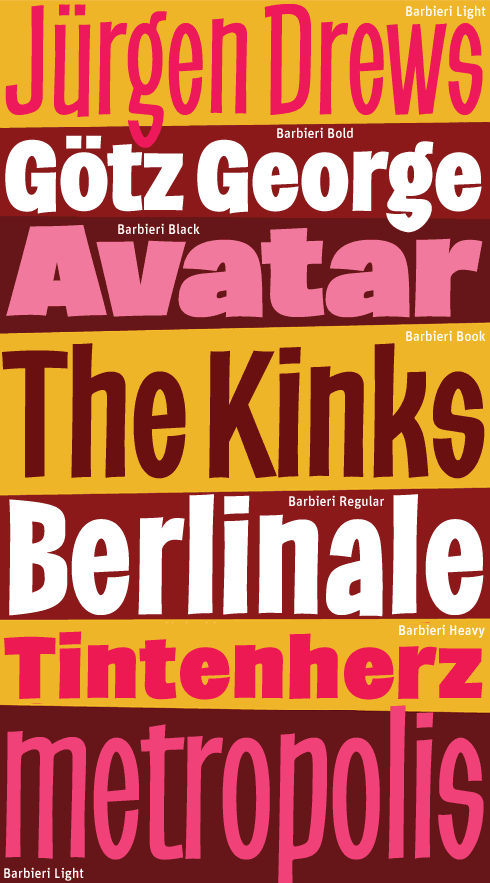
Diese Schriftfamilie braucht nicht viele Worte, deshalb fasse ich mich kurz und stecke meine ganze Energie in das Schriftmuster. Vorlage für Barbieri war eine handgezeichnetes Plakat für eine deutsche Aufführung der Oper »Der Barbier von Bagdad« in den 60er Jahren. Andrés Torresi und Marta Sánchez digitalisierten die Schriftzeichen für die Amsterdamer Foundry ReType und bauten sie zu einer sechsköpfigen Familie aus, mit den Strichstärken Light, Regular, Book, Bold, Black und Heavy.
Mich hat Barbieri sofort an die Typografie einer alten BRAVO erinnert, freilich mit etwas mehr Raffinesse in den Buchstabenformen als damals, wo doch eher existierende Standardschriften mit Photosatz-Effekten versehen wurden. Die Arbeit mit den 6 Barbierei-Schnitten macht ungeheuren Spaß, weil sie unmittelbar Erfolgserlebnisse bescheren. Gerade das Zusammenspiel der Strichstärken öffnet überraschende Gestaltungswege.